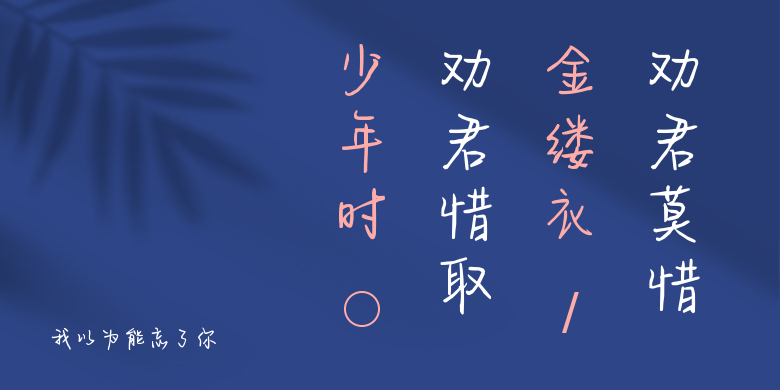
我以为能忘了你
我以为能忘了你,这款字体结构工整、笔画清晰,兼顾美观与易读性,适用于标题、正文、海报、包装、LOGO 等多种场景。字形优雅稳定,风格百搭耐看,适配日常排版与创意设计,让文字呈现更舒适、更具质感。我以为能忘了你一笔一画,皆是细节,以均衡的比例、流畅的线条打造舒适视觉体验,字形端正大气,风格简约现代。无论是商业设计、品牌宣传还是日常排版,都能轻松驾驭,让文字更有格调与力量。我以为能忘了你字体下载。